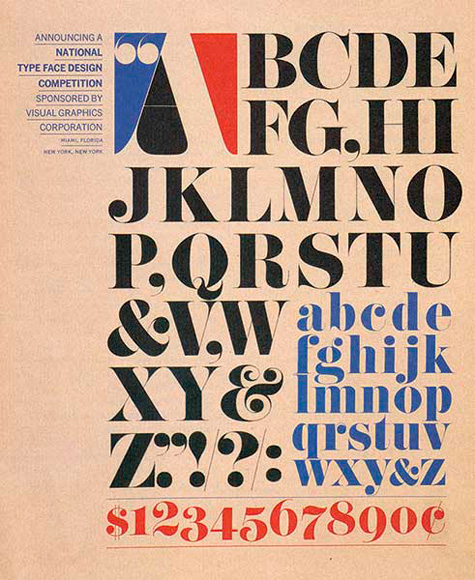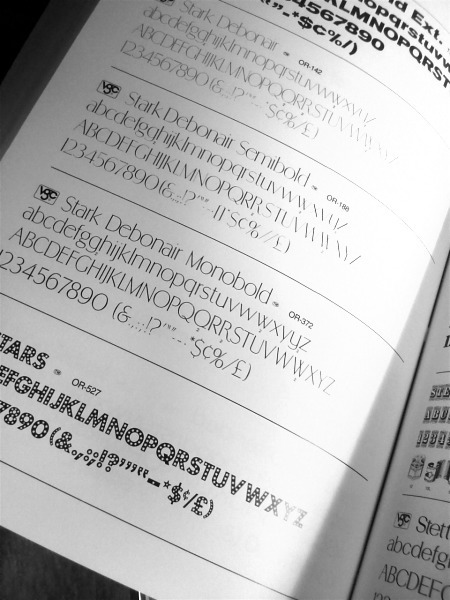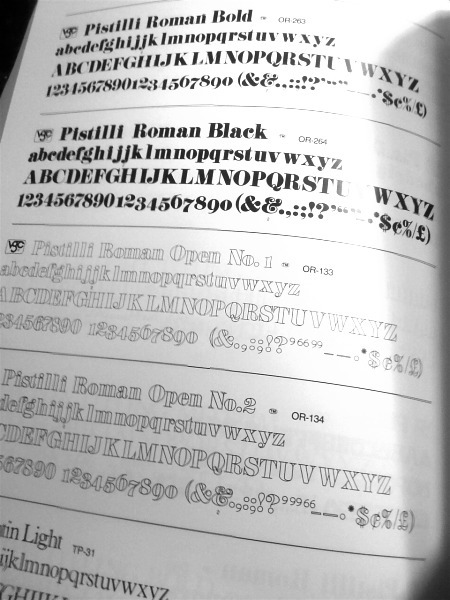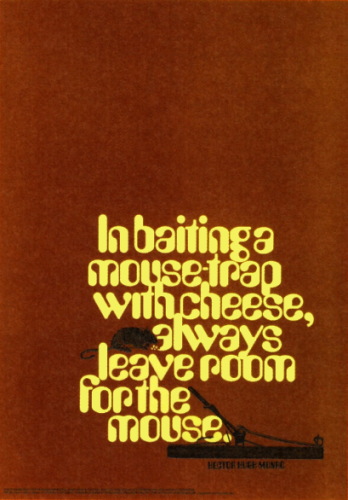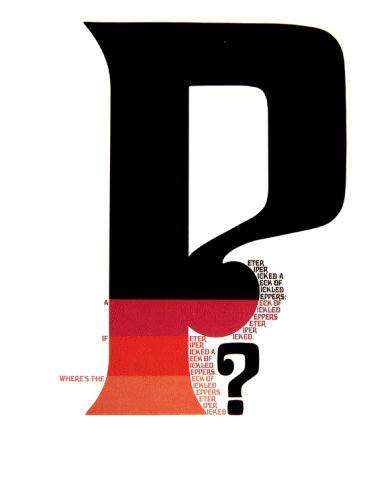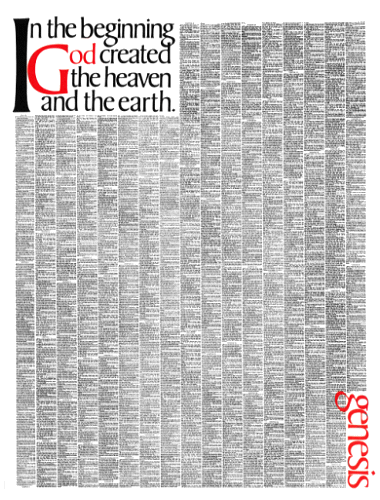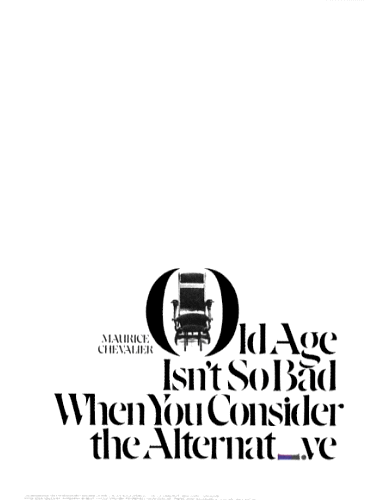
アメリカの古本屋に注文していた『VGC Alphabet Library』が届いた。
Visual Graphics Corporation (以下、VGC)といえば、フォント「Serpentine」が今でも人気ですね。
同社の見本帳は1976年からリリースされていて、今回購入したものは1990年の最終版。
490ページ、2045書体を掲載。
名前は知ってたけど見たことのなかったものなど、フォント化されていない書体が満載です。
『モンセン・スタンダード欧文書体清刷集』は、この見本帳がベースになっているようです。
幻のレア書体「Tiffany with Swashes」(「Tiffany」にスワッシュを施したもの)も
VGC のカスタム書体のようですが、
残念ながらこのカタログには載っていませんでした。
■VGCについて
1959年、マイアミのマレー・フリーデル(Murray
Friedel)が「PhotoTypositor」という写植機を開発。
さらに同氏によって Visual Graphics Corporation が設立されました。
このマシンは多くのデザイナーを魅了し、同社のコンサルタントには、
後にハーブ・ルバーリンと ITC を設立するアーロン・バーンズ(Aaron Burns)が就任しました。
'61年、フォルクスワーゲンの広告キャンペーンで知られる米国の広告会社 Doyle Dane Bernbach が
PhotoTypositor を最初に使用したようです。
また、PhotoTypositor によって、IBM, Mobil, Manhattan Bank などのロゴや
「CBS Didot」などのカスタム・アルファベットが誕生しました。
'64年、VGC 初の書体「Pistilli Roman」をリリース。
このレア書体は、ファッション誌『Self Service Magazine』でよく使われています。
'65年、VGC 主催による第1回タイプフェイス・コンペティションが開催。
審査員はルバーリンをはじめ、Paul Rand, Lucian Bernhard, Will Burtin,
Alvin Eisenman, Bradbury Thompson, Arnold Bank など、錚々たるデザイナーが参加しました。
ルバーリンによって告知ポスターと、入選者の書体を使ったポスターがデザインされました。
01.
Pistilli
Roman を使ったコンペ開催の告知ポスター
02. Davida by
Louis Minott, 1965
03. Solitaire by John W. Denzler, 1965 |
04. Visa by
Raphael Boguslav, 1966
05.
Amelia by Stan Davis, 1966
06.
Arrow by Walter J. Diethelm, 1966 |